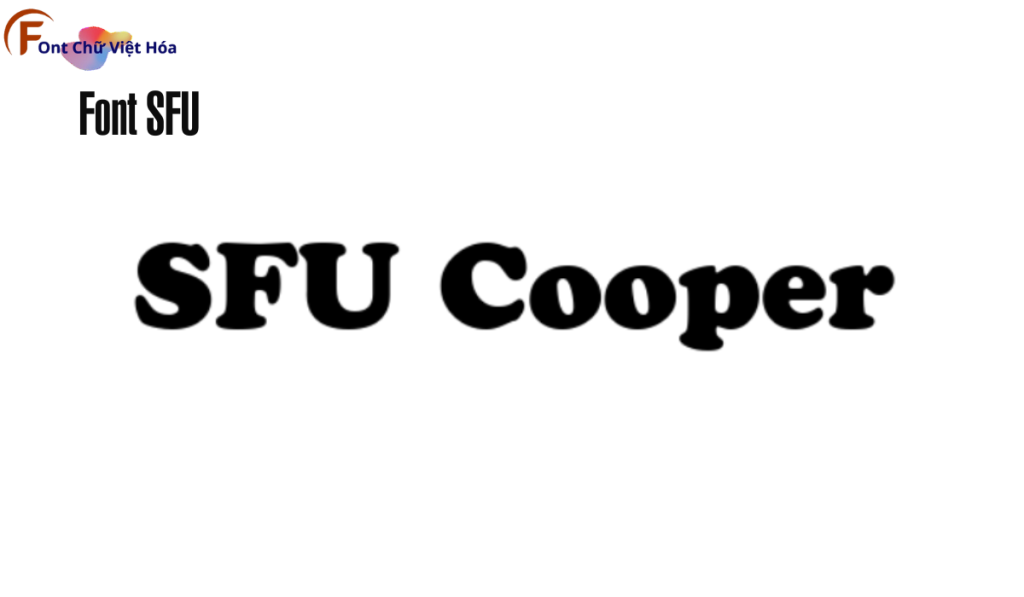
Font SFU Cooper Việt Hóa
Tác giả: Cooper Black
Bộ Font: SFU
Phân loại: Cá tính, Độc đáo
Kiểu chữ: Có chân
Độ dày: Đậm (Bold)
Font SFU Cooper Việt Hóa, thuộc bộ font SFU, mang phong cách serif cổ điển với các đường nét thanh thoát và tinh tế. Font này được thiết kế nhằm mục tiêu tạo ra sự sang trọng và dễ đọc, đặc biệt phù hợp cho các thiết kế như sách, báo, và tài liệu. Đặc điểm hình dạng của SFU Cooper là các đường nét rõ ràng và tỷ lệ chữ cân đối, giúp tạo ấn tượng thị giác mạnh mẽ và tối ưu hóa không gian trong thiết kế. Font này cũng đã được Việt hóa, mang đến sự linh hoạt và tiện dụng cho các dự án thiết kế bằng tiếng Việt, giúp người dùng dễ dàng tiếp cận và sử dụng.